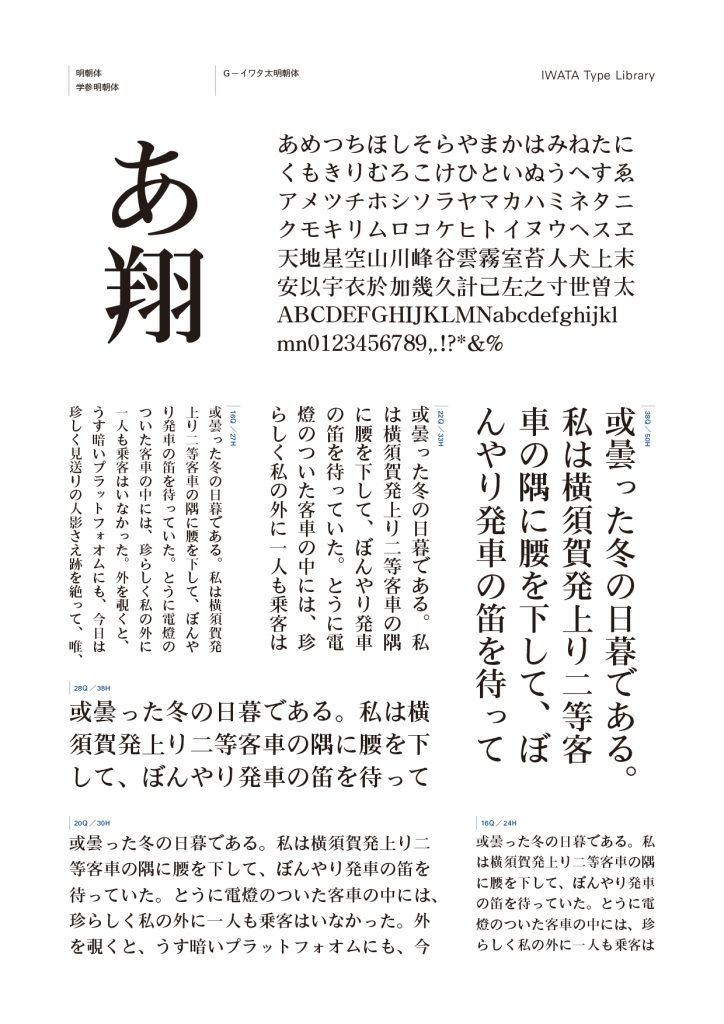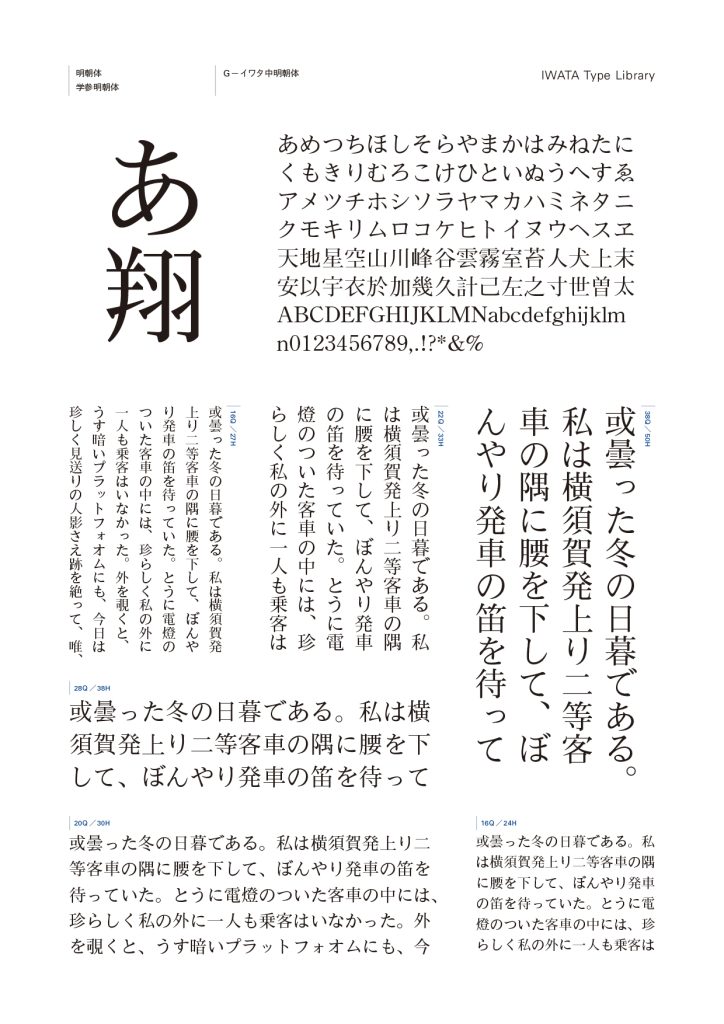
学参明朝体
G−イワタ中明朝体
G−イワタ太明朝体
教科書等の教育に関する著作物、あるいは教育現場にて制作される問題集、副読本等の制作に使用されることを目的として開発されました。
教育漢字1,006文字についてハネ・トメ・押さえ・筆順等を文部科学省の学習指導要領の字形に準拠して制作されたフォントです。小学校の教科書・ドリル・学習参考書に最適です。プロフェッショナルな学習組版に必要な外字1,036文字も付いています。